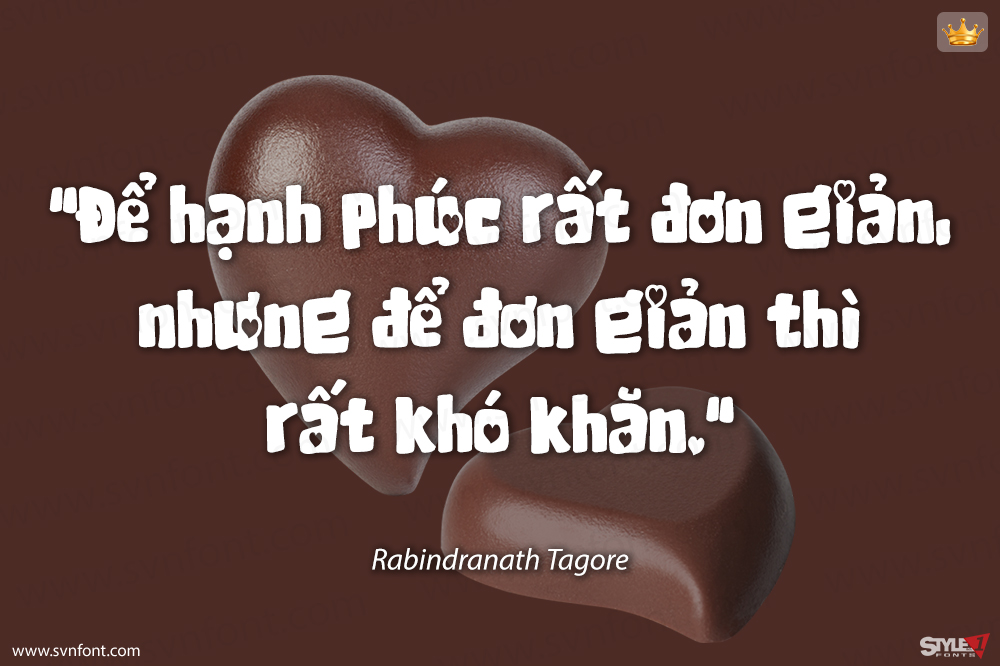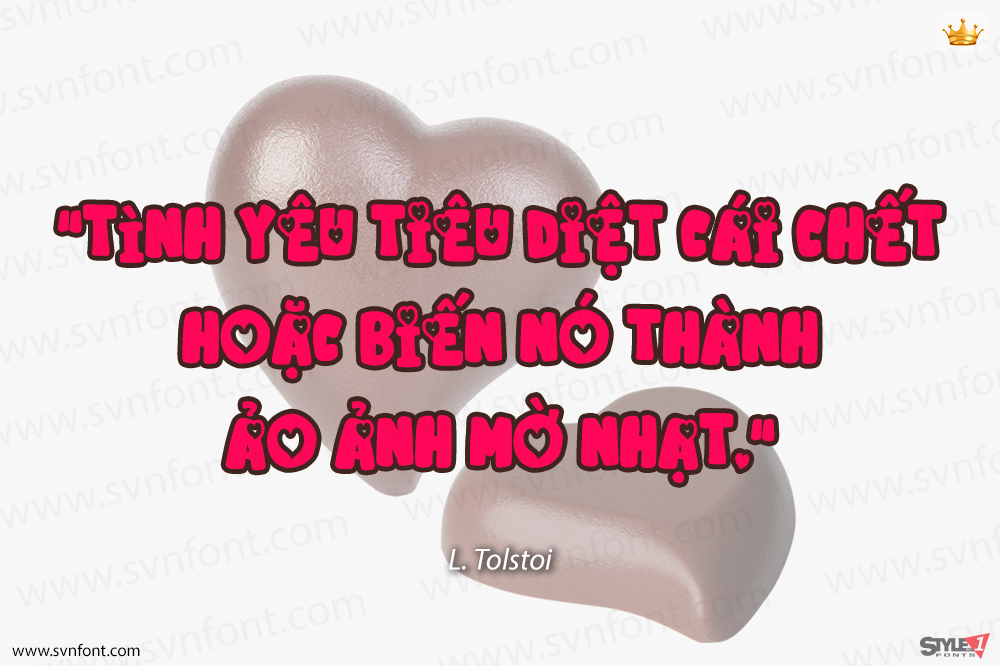
Heart Shaped Chocolate là một phông chữ vui nhộn và kỳ lạ dành cho Ngày lễ Tình nhân. Bạn có thể sử dụng nó cho bất cứ thứ gì, từ áo phông, thiết kế sách thiếu nhi và thiệp chúc mừng đến nhãn dán và áp phích, hoặc bất cứ thứ gì cần một nét giản dị. Hãy yêu thích phong cách cực kỳ linh hoạt của nó và sử dụng nó để tạo ra những thiết kế đáng yêu!